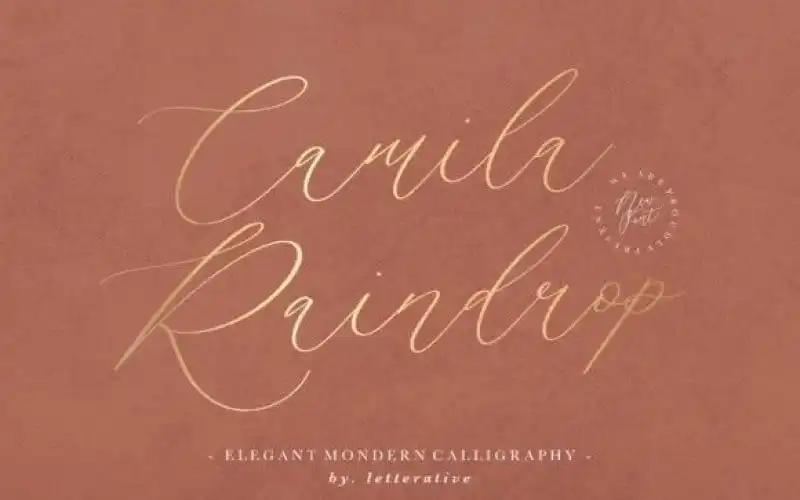
Camila Raindrop Script Font – Download Grátis
A Camila Raindrop Script Font é uma criação única do designer Hamilton, perfeita para aqueles que buscam uma fonte escrita a mão com estilo inconfundível e personalidade vibrante. Esse script tem um toque de autenticidade na sua escrita a mão, trazendo consigo aquela sensação elegante e divertida. Perfeito tanto para usar em logomarcas, como em outros formatos formais como cartões de convite, rótulos, selos, revistas, livros, cartas de casamento, embalagens ou até mesmo anúncios, a Camila Raindrop Script Font traz uma nova dimensão à sua identidade visual. Sua elegância e vivacidade irão destacar seus projetos criativos com um toque especial que apenas essa fonte pode oferecer. Você vai amar o tom leve e divertido que ela adiciona a suas criações, tornando-as ainda mais memoráveis. Caso deseje adicionar essa fonte à sua paleta de recursos gráficos, garanta a sua versão hoje!